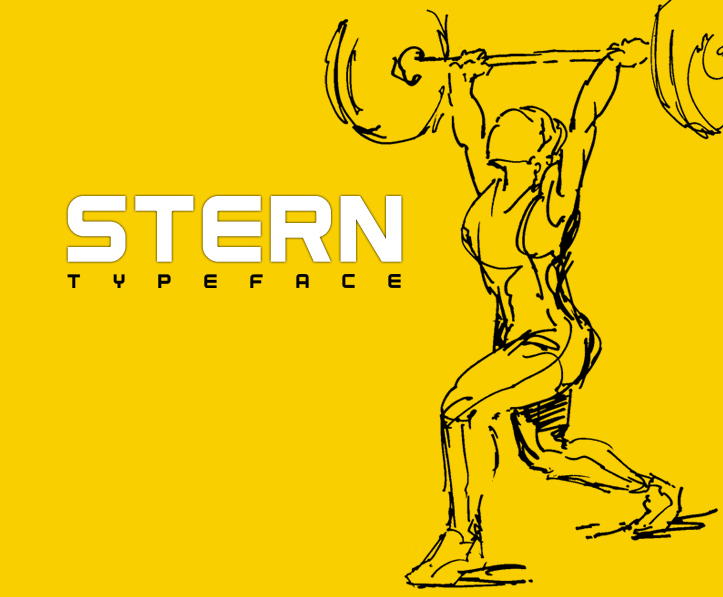
A fonte ‘STERN Font’ é uma tipografia sans-serif para uso com letras maiúsculas que traz a essência moderna e assertiva do tipo digital contemporâneo. Cada caractere, ou glyph como Hamilton define, foi projetado cuidadosamente para oferecer formas mais refinadas, tornando-a especialmente adequada para ilustrações, logotipos e todo o tipo de trabalho tipográfico. Não importa se você está criando um logo memorável, desenhando uma gráfica impactante ou simplesmente adicionando aperitivos tipográficos a sua produção de arte digital, ‘STERN Font’ trará um toque moderno e poderoso à sua criação. Completamente em letras maiúsculas, esta fonte é perfeita para ambientes onde o uso da maiúscula predomina, seja no topo de uma página ou na marca registrada de seu próximo projeto gráfico.